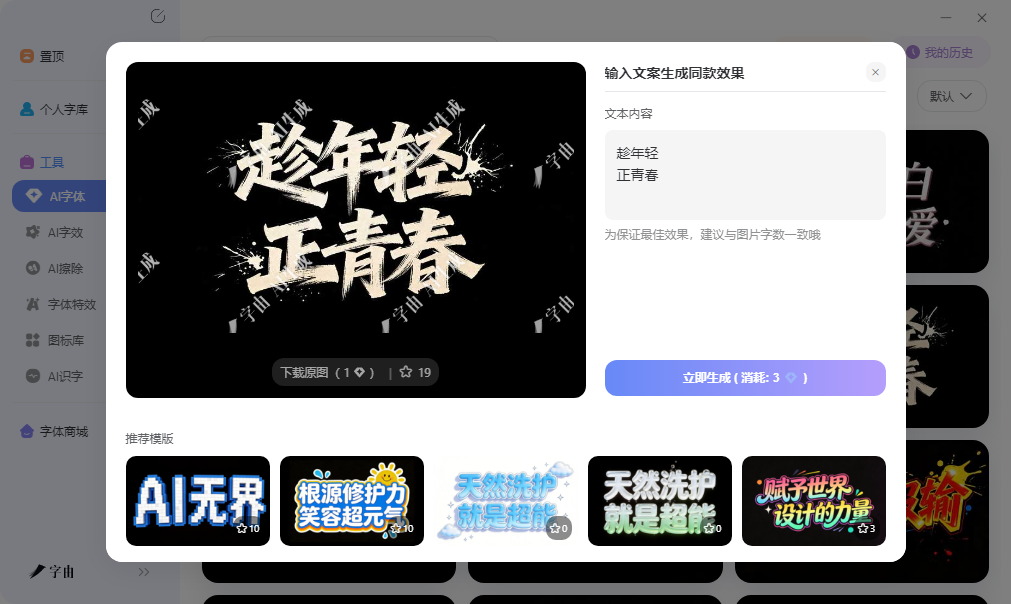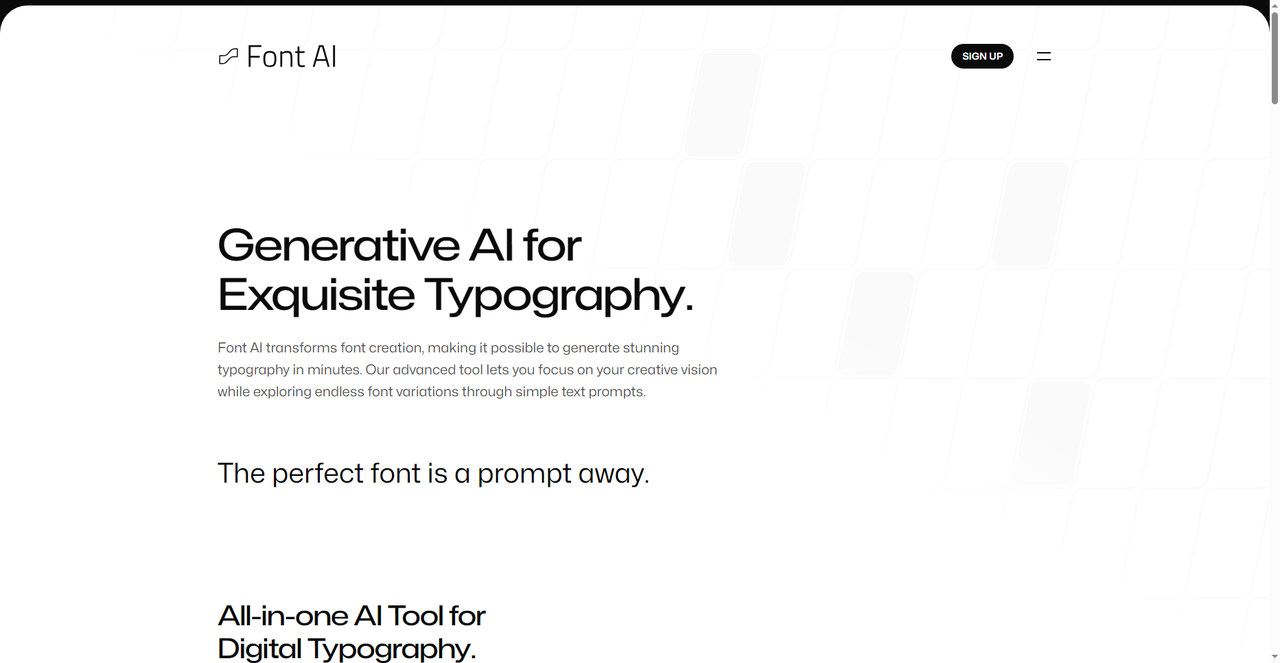
免费在线艺术字在线生成,不用再为海报标题设计发愁
每次做海报,标题字的效果总是最耗时间的环节。选字体、加发光、调阴影,参数改来改去看不出差别。现在有很多免费在线工具,输入文字就能直接生成艺术字图片。这篇文章测试了5款工具,有的提供现成模板直接套用,有的用文字描述让AI生成,还有的可以一键复制艺术风格文本。不需要设计基础。每款工具的操作方式、输出格式和适用场景不同,按自己的需求选用即可。
字由的AI字体功能是目前操作最简单的一类艺术字生成方式。用户不需要理解发光、阴影、渐变等参数含义,也不需要从零开始设计。打开字由客户端,进入AI工具下的AI字体页面。
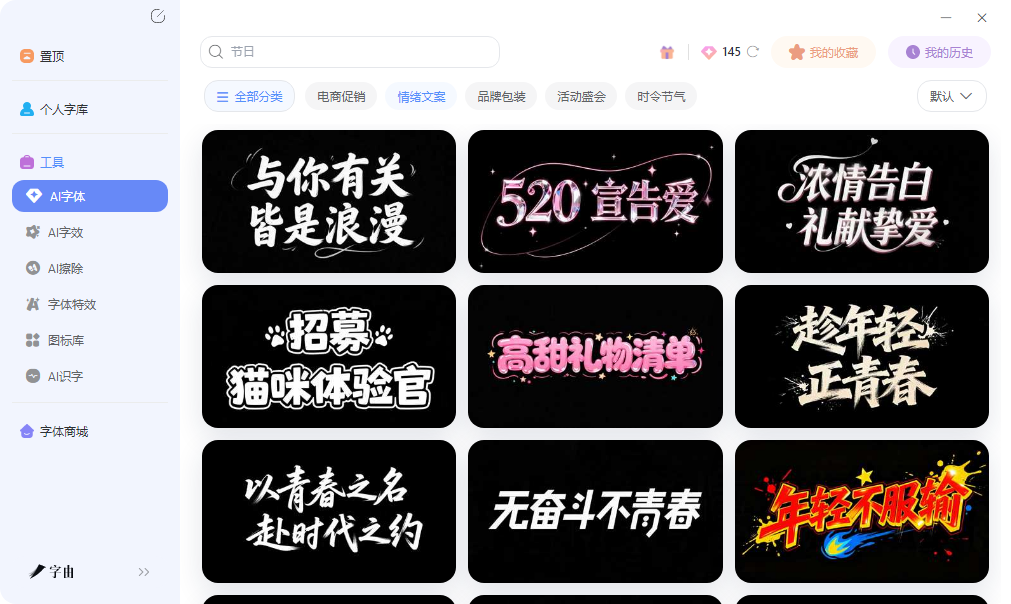
进入标签栏按风格分类,这些模板的字体、排版、特效参数已经由专业设计师调校完成。用户选择一个分类,浏览该分类下的模板。鼠标悬停时预览图会显示用户输入的文字效果。用户输入自己的文案后点击生成按钮,系统在10到15秒内输出一张PNG格式图片。图片背景透明,可以直接用于海报、封面或Banner。
字由的模板覆盖了大部分常见设计需求。电商促销分类适合大促主图标题,字体重、色彩鲜艳、冲击力强,用户输入“限时五折”“最后一天”等文案即可快速出图。霓虹灯分类适合夜店活动或科技感海报,每个字母模拟真实灯管的弯曲和反光,适合做派对邀请函或电竞比赛封面。
生成结果可以下载为透明背景的PNG,支持直接拖入PS、Canva、剪映等软件。如果对生成结果不满意,可以更换模板重新生成,或者调整文案长度使其接近模板示例的字符数,以保持排版效果。
2、Font AI
第二个工具是Font AI。它提供了一种完全不同的艺术字生成方式:用户不需要选择现成模板,而是用文字描述想要的效果,或上传参考图,AI根据输入生成定制字体。该工具的核心功能包括字体检测、无源文件编辑、字体选择和定制四个方面。用户上传一张包含文字的图片,系统从字体库中匹配。如果找不到完全匹配的字体,AI会生成一款新的相似字体。这个功能对于看到喜欢的字体但不知道名称的场景非常有用。无源文件编辑功能:用户上传一张图片,即使没有原始字体文件,也可以修改图片中的文字内容。这解决了AI图像生成工具输出的图片文字不可编辑的问题。
Font AI的操作方式比字由更灵活,但需要用户有一定的描述能力。输入的提示词越具体,生成结果越接近预期。例如“细长优雅的手写体,带有装饰性连笔”比“好看的手写体”更容易得到满意结果。该工具适合有明确创意想法但找不到现成模板的用户。
3、fontish
第三个工具是fontish。它与Font AI类似,但更进一步:用户输入文字描述或上传参考图后,系统生成一套完整的字体家族,包括常规、粗体、斜体等多个字重变体。普通艺术字生成器只输出一张标题图,fontish输出的是一个可安装的字体文件。用户可以将生成的字体安装到电脑中,在Word、PS等软件中反复使用。
fontish的定位是生产级字体设计工具,适合需要为品牌定制专属字体的设计师或企业。例如一家咖啡店想要一套用于菜单、招牌、纸杯的手写风格字体,可以使用fontish上传几张参考图,AI生成多款变体,用户选择最合适的一款导出安装。生成的字体文件是标准的TTF或OTF格式,兼容Windows和macOS。
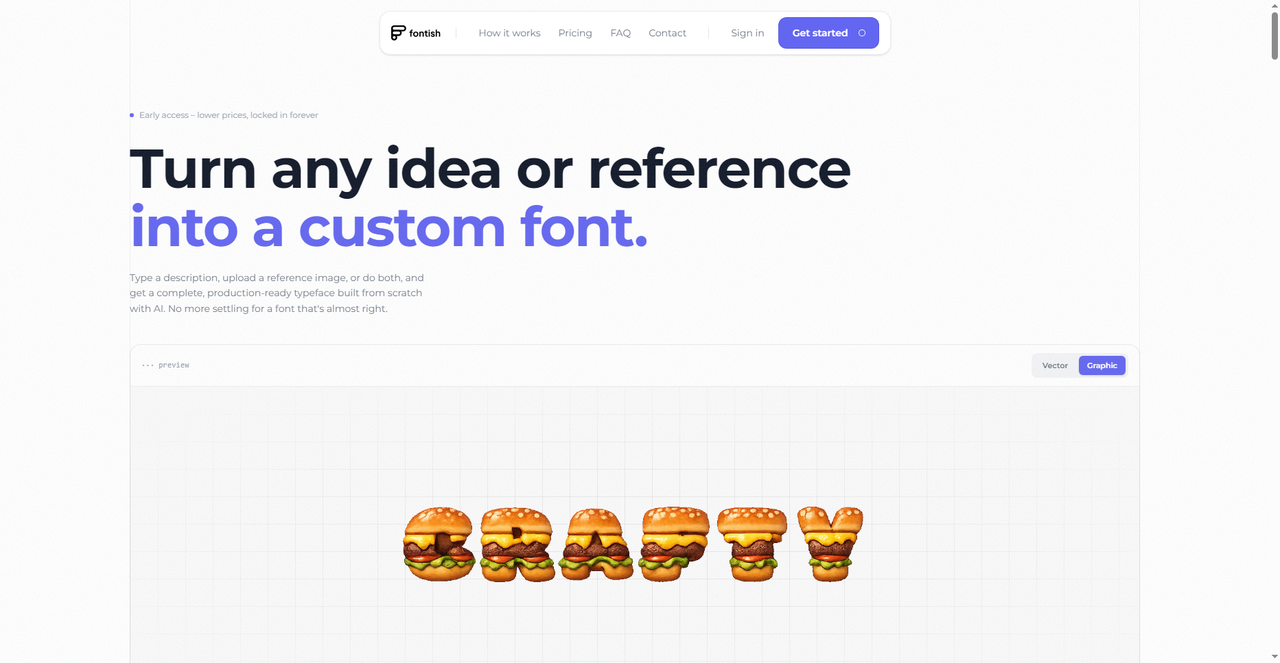
4、FontGenerator
第四个网站是FontGenerator。它不生成图片,而是将普通文字转换成Unicode艺术字符。用户输入文字后,系统展示多种艺术风格样式,包括花体、哥特体、双线体等。每种样式旁边有复制按钮,点击即可复制转换后的文本。
用户可以将复制的内容直接粘贴到社交媒体帖子、个人简介、聊天消息中,接收方不需要安装任何字体即可看到艺术字效果。这个工具适合需要在不支持图片的场合使用艺术字,比如社交平台评论区、游戏昵称、论坛签名等。完全免费,无需注册
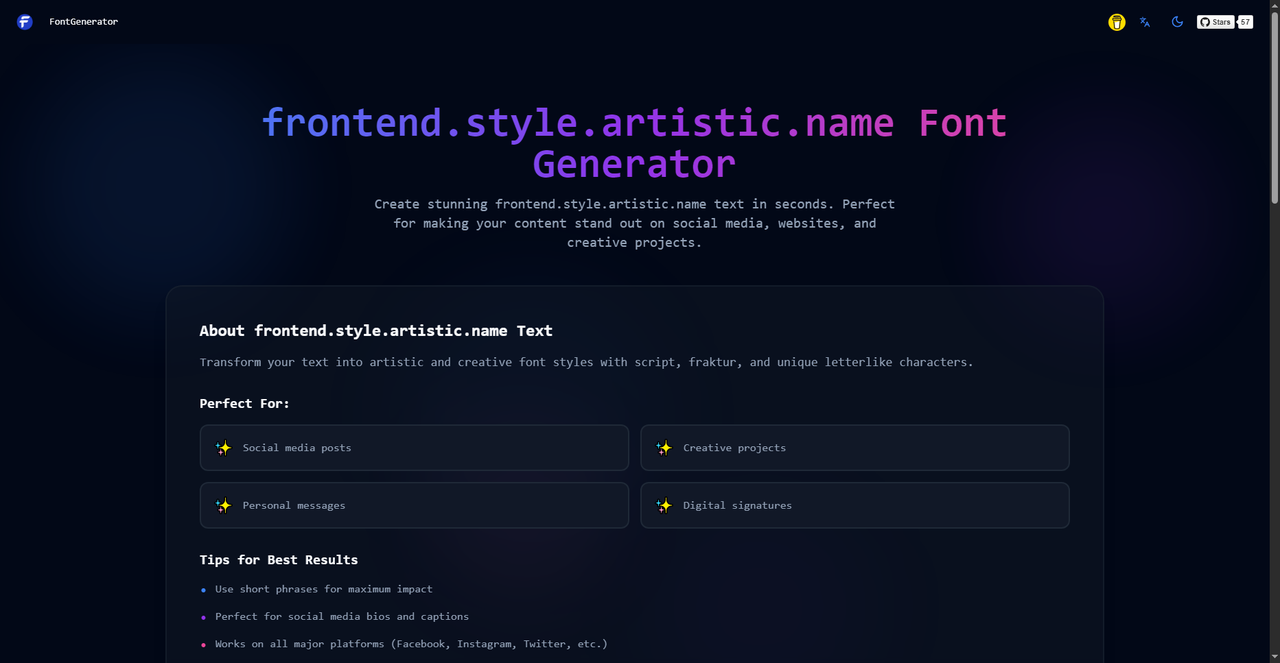
5、ArtFont
第五个工具是ArtFont。它提供了200多套AI艺术字模板,覆盖书法、涂鸦、霓虹、极简、复古等风格。用户输入文字后选择一个模板,系统生成高清艺术字图片,支持2K和4K导出。新用户注册赠送10个免费积分,每次生成消耗一定积分。免费积分用完后可以通过分享或付费获取。
ArtFont的模板风格与字由有重叠但也有差异。字由的模板更偏向商业设计场景(电商促销、品牌海报),ArtFont的模板更偏向艺术创作和社交媒体配图。首页展示的分类包括Calligraphy(书法)、Street Art(涂鸦)、Neon Glow(霓虹)、Elegant Minimal(极简优雅)、Retro(复古)等。
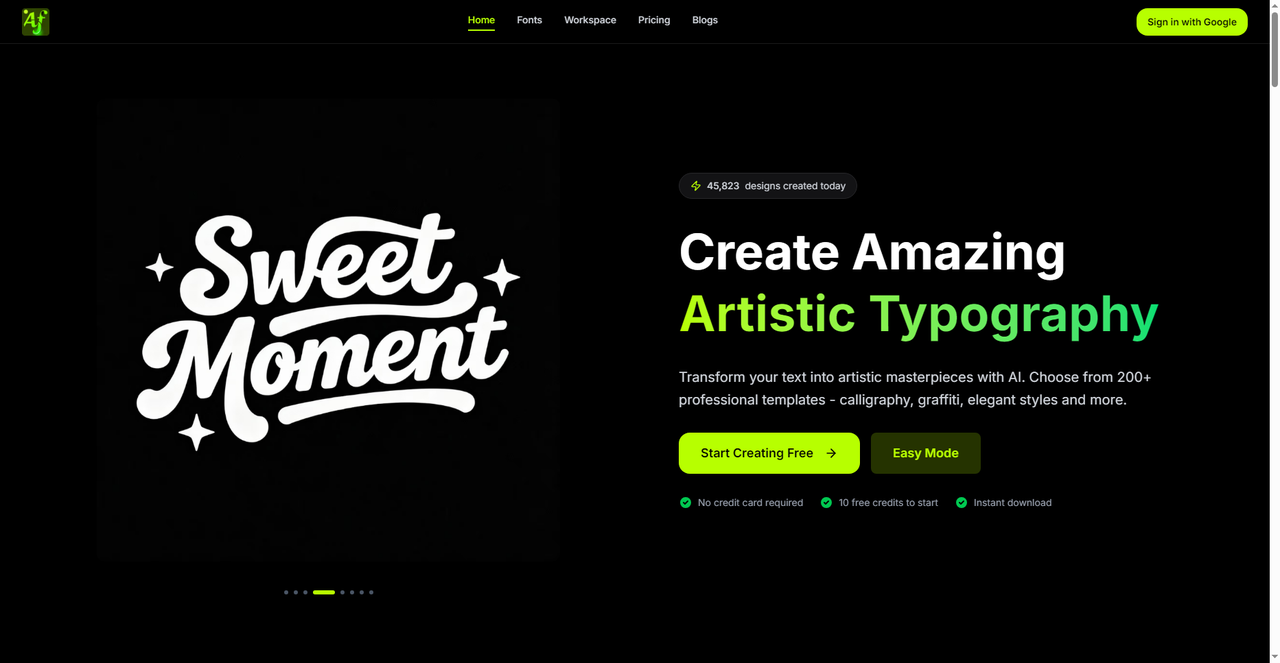
五款工具都试下来,字由最适合不想折腾的用户,模板多且免费额度够用。Font AI和fontish适合愿意写提示词、想要独特效果的人。FontGenerator解决社交媒体花体字需求,最轻量。ArtFont适合需要高分辨率输出的场景。根据自己手头的项目选一个,不用纠结哪个最好。输入文字,点生成,几分钟搞定标题图。